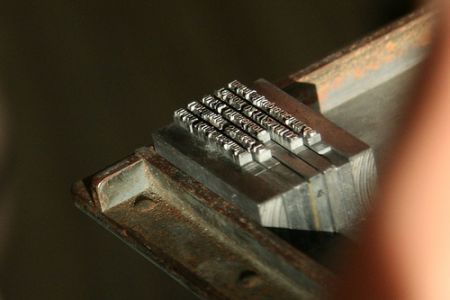
Wei ss nicht mehr, wo ich das gelesen habe, fand es aber total logisch: Das Untereinanderschreiben von Nummern führt dazu, dass du leichter in der Zeile verrutscht (FRaxton im Ohr). Wichtig ist die vertikale Linie für die Augenbewegung, denn man macht keinen Strich unter Telefon und Fax und schreibt die Summe darunter, fand ich witzig ...
Mit Bleisatz kenn ich mich nicht aus, aber "spationieren" geht, glaube ich. Kannst du doch mit Ziffern auch machen. Und Zeilenabstände erweitern müßte doch da auch gehen, oder nicht?
Die Din schreibt zwar nichts genaues mehr vor, aber die Gruppierung der Telefonnummern vom Bleisetzer erschließen sich mir irgendwie nicht. Zweiergruppen oder Dreier- und wieso die Vorwahl nicht auch?
Ich finde den Namen in fetten Gemeinen besser, weniger majestätisch-preußisch und ein Gegengewicht im Grauwert zum Logo.
Typo nach DIN - ich weiss nicht. Aber Bleisetzer hat die Nummern inhaltlich grupiiert, nicht formal. Find ich oprima. So kann man sie sich besser merken, wahrscheinlich sagt er sie so auch am Telefopn an, oder Bleisetzer, hab ich recht oder ja?
Warum braucht das Logo ein Gegengewicht?
Ja, Telefonnummern werden lt. DIN in Gruppen von jeweils zwei Ziffern von hinten abgetrennt.
Abgewichen davon bin ich aus folgendem Grund:
Der mnemotechnische Vorteil schien mir wichtiger bei einer Abtrenung:
99 77 948
Gleichzeitig suggeriert das eine Telefonanlage mit einer Hauptanschluß-Nummer 99 77 - 0 und der Nebenstelle 948. Das empfinde ich bei einem Bleisatz-Magazin als kleinen Scherz, der mir gefällt.
Gleiches gilt für die Faxnummer:
12 567 38
Auch hier ist der mnemotechnische Effekt für mich wichtiger als die Einhaltung der DIN, siehe:
12 567 38
1 25 67 38
99 77 948
9 97 79 48
Daß die DIN bei der Vorwahl 02102 nicht eingehalten wird, ist einzig und allein eine respektvolle Verbeugung vor dem Mediengestalter, der das Gesamtdesign des PBM nach meinen Vorgaben entwickelt hat.
Der lehnt solche Normen ab, ich dagegen befürworte sie vom Grunde her.
Und weil er mir in teilweise heftigen Diskussionen schon bei der Gestaltung hat nachgeben müssen (Wer zahlt, bestimmt (manchmal)), habe ich ihm diese Schrulligkeit durchgehen lassen. Ich selbst hätte die Vorwahl 0 21 02 abgetrennt.
Ja, genau. Deshalb mnemotechnisch.
Es spricht und merkt sich so auch leichter.
Die Frage mit dem Gegengewicht habe ich nicht verstanden.
Indra hatte gemeint, die fette Schrift ist ein gegengewicht zum logo. Deswegen meine Frage: Warum braucht das Logo ein gegengewicht?
Das verstehe ich schon, dass man die Nummern lieber anders gruppiert, um sie sich besser zu merken, es gibt dazu auch keine genauen Bestimmungen mehr. Aber wenn man sich ein Prinzip ausdenkt, sollte man es auf einer Karte auch überall umsetzen.
Dann hätte ich Tel: 99 77 948 und Fax: 12 56 738 gesetzt.
Die Vorwahl en bloc davor sieht irgendwie komisch aus.
Aber Du hast ja jetzt eine Gelegenheit zum umsetzen.
Mein Einwurf zum fetten Namen bezog sich auf den schwarzen und weißen Streifen in der Flagge, der dadurch noch einmal aufgenommen wird und man einen optischen Anhaltspunkt hat, wo man als erstes und wichtigstes hin schauen soll.
Dreistellige Zahlen funktionieren am Telefon überhaupt nicht. Ist NEUNHUNDERTACHTUNDVIERZIG nun 900 48 oder 948?
Die zweistellige Trennung (die übrigens nicht mehr DIN-gemäß ist) zu brechen, ist im Einzelfall völlig legitim. Aber wenn so bei Telefon und Fax eine andere Teilung entsteht, finde ich das auch eher abträglich.
Ich wette, Bleisetzer sagt seine Nummer so:
neun neun - sieben sieben - neun vier acht
Indra, danke für die ASntwort. Meinst du, auf meinem versuch würde man den Namen nicht sehen? Ich finde die Linien auf dem gedruckten so wirr, dass ich mehr auf die Linien gucken würde und mich fragen: Was soll mir das denn jetzt sagen? Ist das die preusssische bahn? In meinem kleinen versuch guibt es ja nur zwei Punkte: Oben und unten. Erst kuckt man oben: Firma. Dann unten: Name. Meinst du, dass die Leute auf meinem versuch den Namen suchen müssen?
Die Vorwahl in einem Block bewirkt, dass man sie sofrt als Vorwahl erkennt. Und bis 5 Ziffern sind Gruppen gut lesbar, sagt "Detailtypografie"
((... ich musste doch noch mal schnell bei Chris Burke nachschauen: Renner hat 1924 schon in einem Probeschnitt für die Futura Mediävalziffern entworfen (als erste Serifenlose überhaupt) und die waren mindestens auf Bestellung auch immer lieferbar. Es gab Versalziffer, Normalziffern auf Halbgeviert, Gemein Ziffern und Bruchziffern. Aber das gehört eigentlich in den »Suche-Futura-Thread« von neulich.))
Gern werden auch immer noch E-Mail-Adressen in die Adressleiste des Browser eingegeben oder E-Mails an www-Adressen verschickt.
Ich schreibe daher immer »E-Mail« und »Webseite« dazu.
Gern werden auch immer noch E-Mail-Adressen in die Adressleiste des Browser eingegeben oder E-Mails an www-Adressen verschickt.